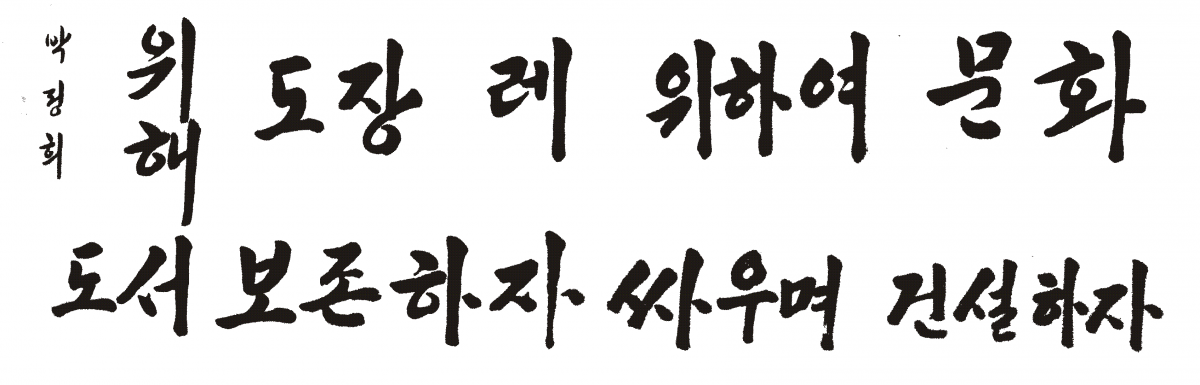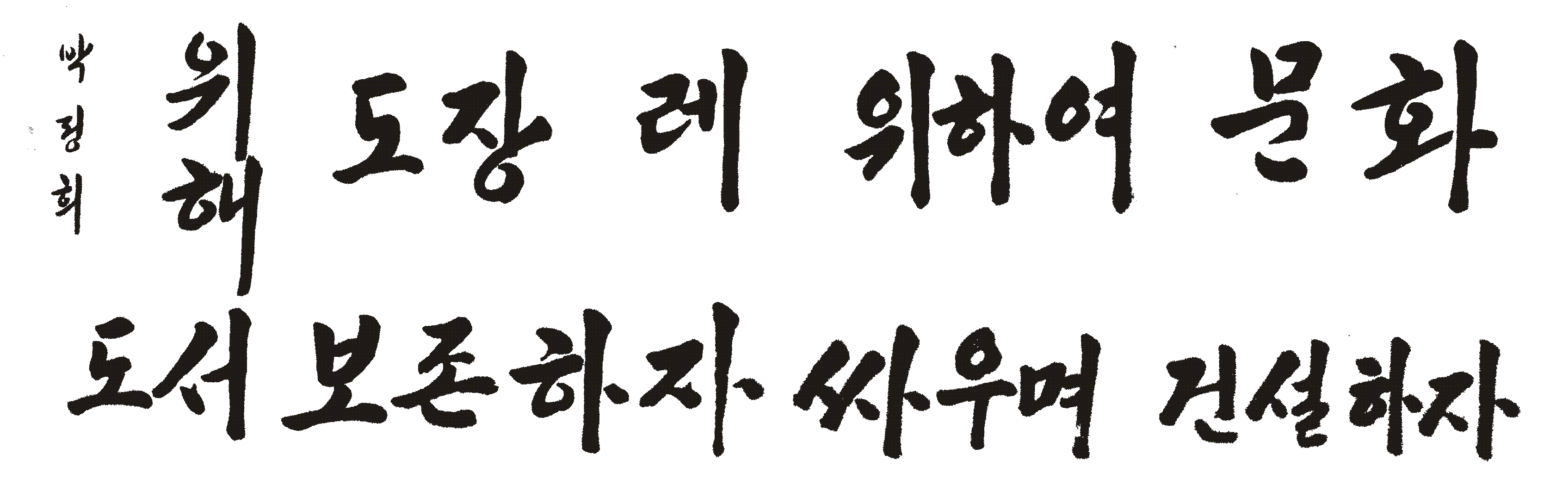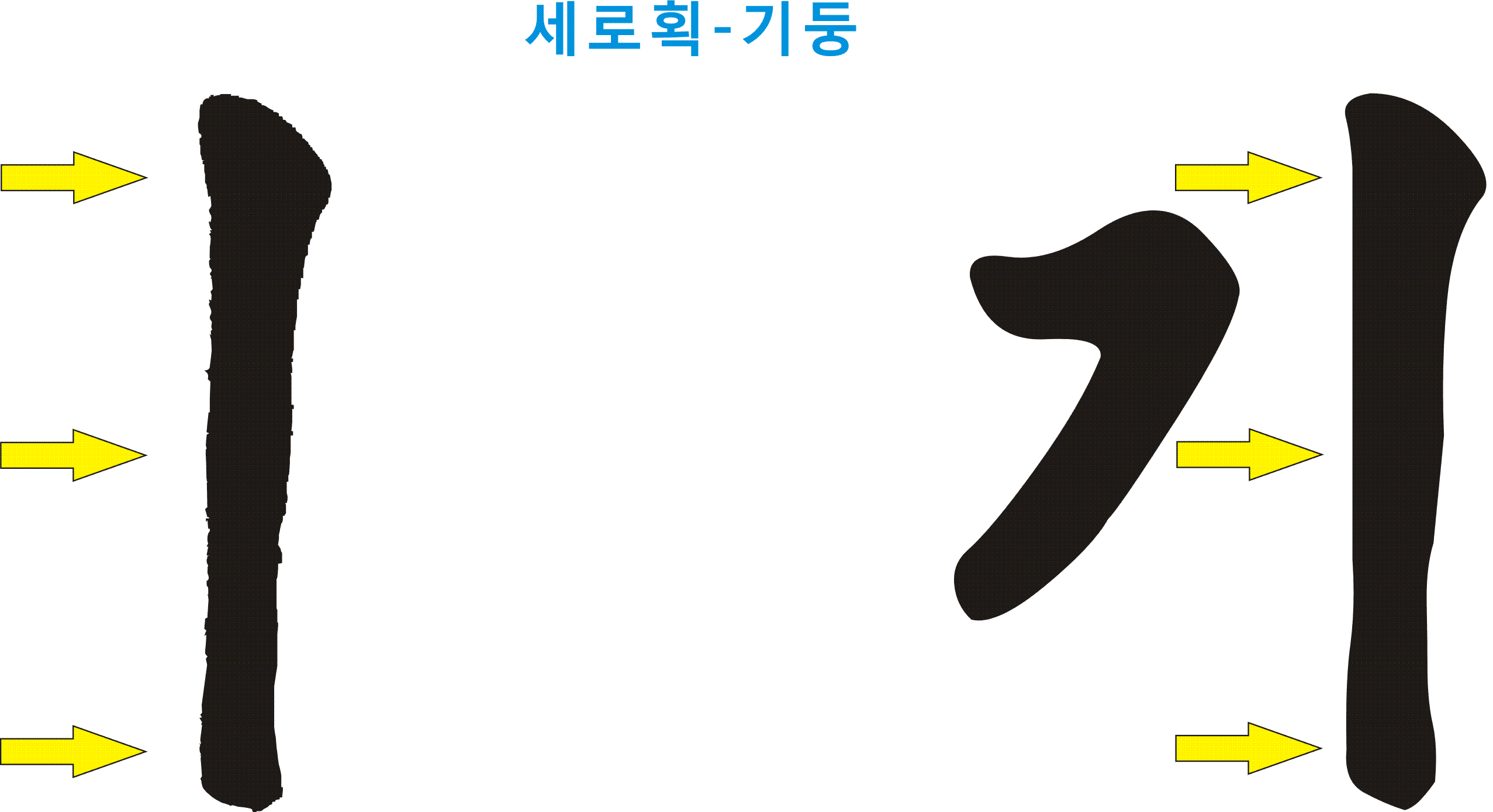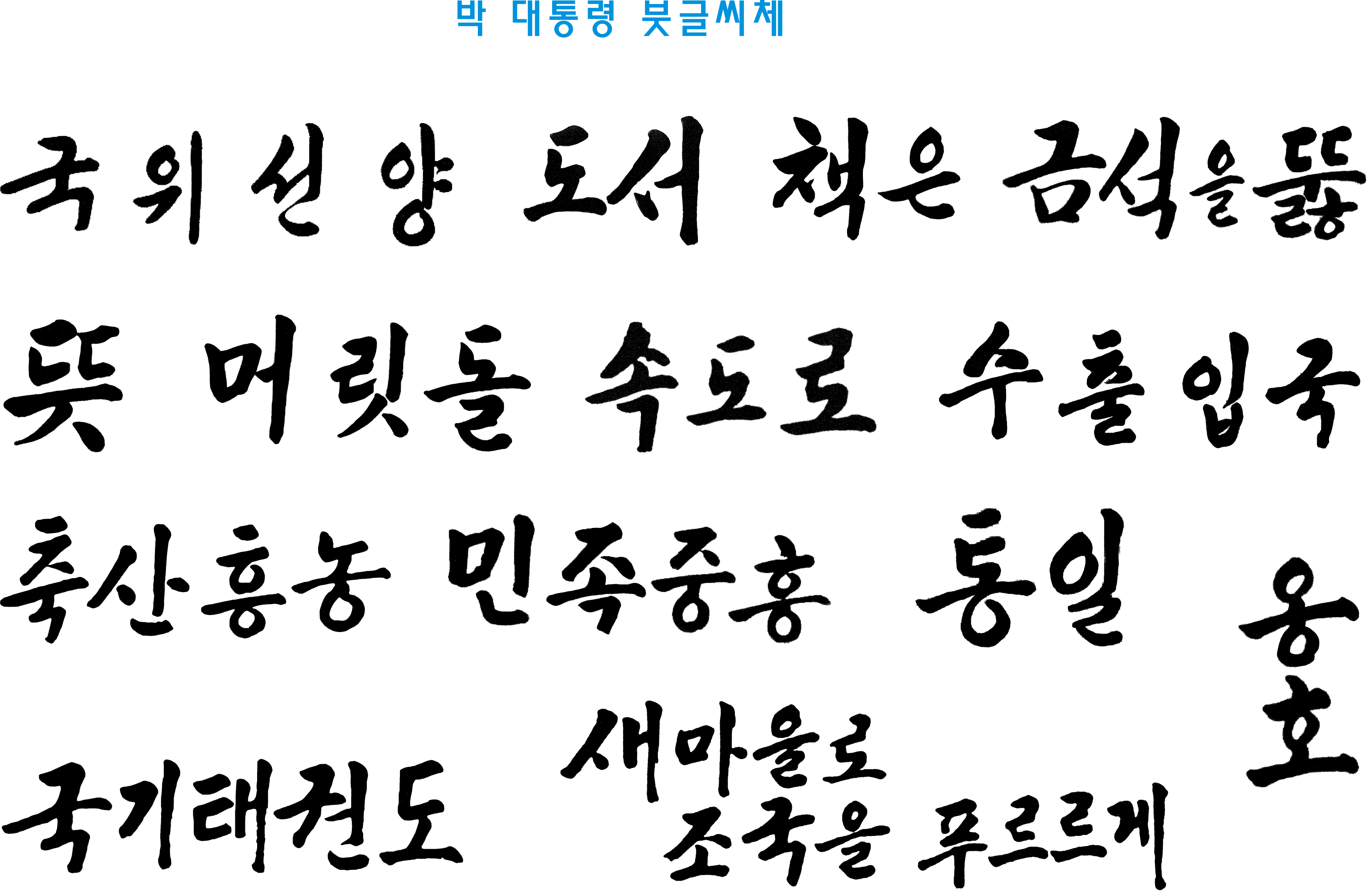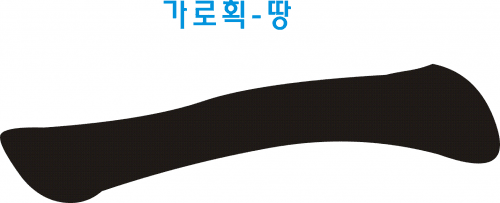
[tip]서체 제작 첫 시작 – 제일 먼저 세로획을 정한다[/tip]
서체를 제작하는데 있어서 디자이너가 제일 먼저 고려해야 할 점은 뭘까? 제작자마다 생각이 다르겠지만, 나는 세로획가로획을 결정 짓는 것이라고 생각한다.
시중에 나와 있는 여러 서체의 세로획가로획을 살펴보고, 자신의 디자인을 구상해 본다.
그러면 박 대통령은 글을 쓸 때, 가로획세로획을 어떻게 쓰는가?
세로획 모양을 알아보기 위해 친필 붓글씨에서 세로로 써 내려간 글씨를 한데 모아 비교해 보았다. 자세히 살펴보면 글자마다 조금씩 다른 것을 알 수 있다.
친필에서는 여러가지 다양한 세로획이 나타나는데, 위의 글씨 중에 세로획만 따로 떼내면 아래와 같이 여러 모양을 볼 수 있다.
그러면 이 중에서 어느 것을 선택할까?
전부 다 사용하면 좋겠지만 컴퓨터가 인식하는 기계적인 언어로 사용하기 위해서는 모든 획을 다 수용할 수 없고 하나의 획으로 결정지어야 한다. 그래서 ‘보존하자‘의 ‘‘에 해당되는 빨간 색 세로획으로 결정하기로 했다.
그 이유는 여러개 중에 가장 미적 감각이 뛰어나고 무게감과 안정감도 있어서 어떤 자모가 옆에 와도 조화를 이루고 기둥 역할도 충분히 할 것 같았다.
선택한 세로획으로 ㄱ ㄴ ㄷ ㄹ ㅁ …. 를 붙여 보았다.
예상대로 잘 어울린다. 이제 이 기둥을 기본으로 하여 ㅏ ㅑ ㅓ ㅕ ㅔ ㅖ ㅐ ㅒ 를 만들어 나갈 것이다.
세로획 기둥은 특별한 느낌을 준다. 글자에 힘을 가한 부분을 자세히 보면, 처음에 붓 끝을 ‘쿡’ 찍고 내리 긋다가, 중간에 힘을 한 번 더 주고 내려가다가, 마지막은 붓을 푹 누르고 바로 자르듯 붓을 ‘툭’ 떼는 것이다. 이러한 방식은 박 대통령만의 고유한 필법으로 여러 곳에서 발견된다.
그리고 또 하나.
| 자로 꼿꼿하게 수직으로 선 것이 아니고 약간 각도가 오른쪽으로 기운 것이 특징이다. 기우림 글씨는 바로 선 글씨보다 강한 메시지를 전달한다.
[tip]다음은 가로획을 정한다[/tip]
박 대통령은 글을 쓸 때, 가로획을 어떻게 쓸까?
가로획 모양을 알아보기 위해 친필 붓글씨에서 옆으로 긋는 글씨를 한데 모아 비교해 보았다. 자세히 살펴보면 글자 위치마다 조금씩 다른 것을 알 수 있다.
옆으로 긋는 모양도 다양하게 나타나는데, 위의 글씨를 가로획만 따로 떼어 내었다.
아래와 같이 한 눈에 볼 수 있도록 비교해 보자.
붓에 힘이 들어가는 부분도 다르고 각도도 다른 것을 느낄 수 있다.
이 중에서 어느 것을 선택할 것인가는 디자이너의 판단이자 고민이다. 전부 다 사용하면 좋겠지만 컴퓨터가 인식하는 기계적인 언어로 사용하기 위해서는 모든 획을 다 수용할 수 없고 하나의 획으로 결정지어야 한다.
이번에는 위의 필체를 조금 응용하여 가로획, 땅에 해당되는 가로 획을 다음과 같이 만들었다.
전체적으로 일정한 각도를 주면서 시작 점과 끝 점에다 힘을 배분하였고, 가운데는 활처럼 휘어져 약간 거칠게 울룩불룩 튀어 나온 형상을 하여 생동감을 부여하였다.
선택한 가로획으로 ㄱ ㄴ ㄷ ㄹ ㅁ …. 를 붙여 보겠다.
무엇보다도 안정감이 최우선이다. 이 글들은 초성과 중성 만으로 조합된 형태이므로 높이를 낮게 설정하였다.
이제 기본 땅을 바탕으로 ㅗ ㅜ ㅛ ㅠ 를 만들어 나갈 것이다.
이상으로 서체 제작에 있어서 제일 먼저 고려해야 할 점에 대하여 ‘박정희 폰트’를 예로 들어 살펴 보았습니다.